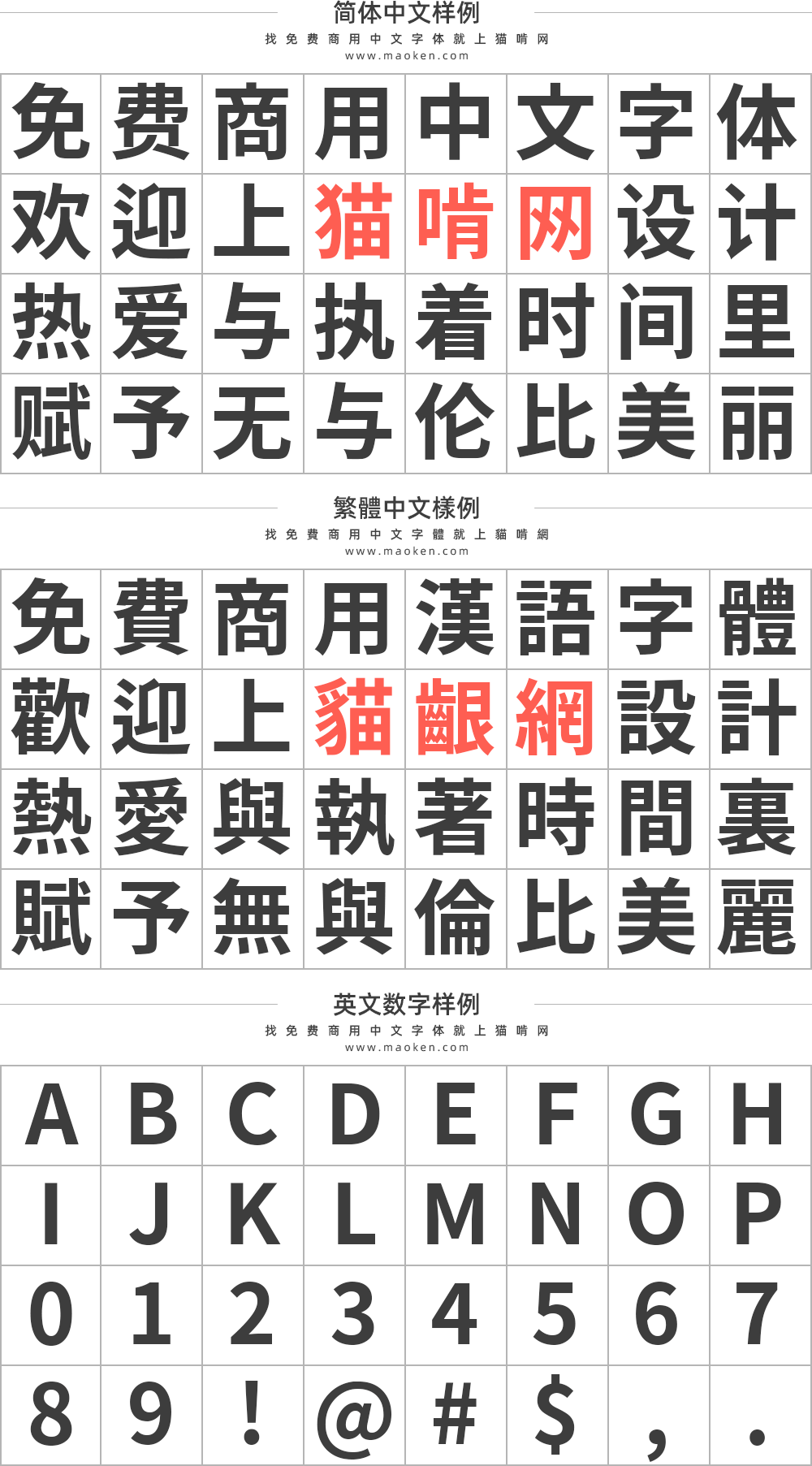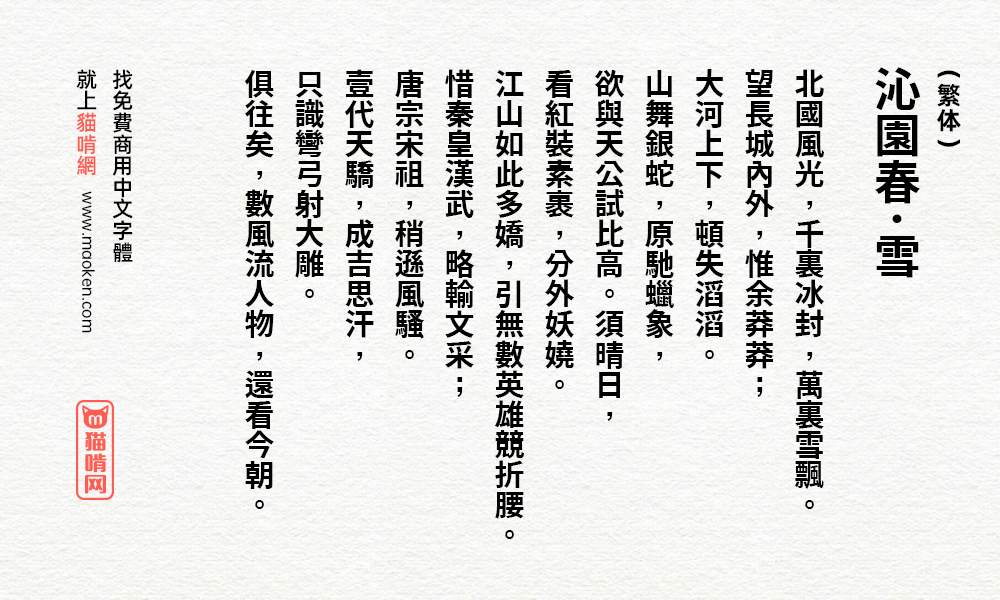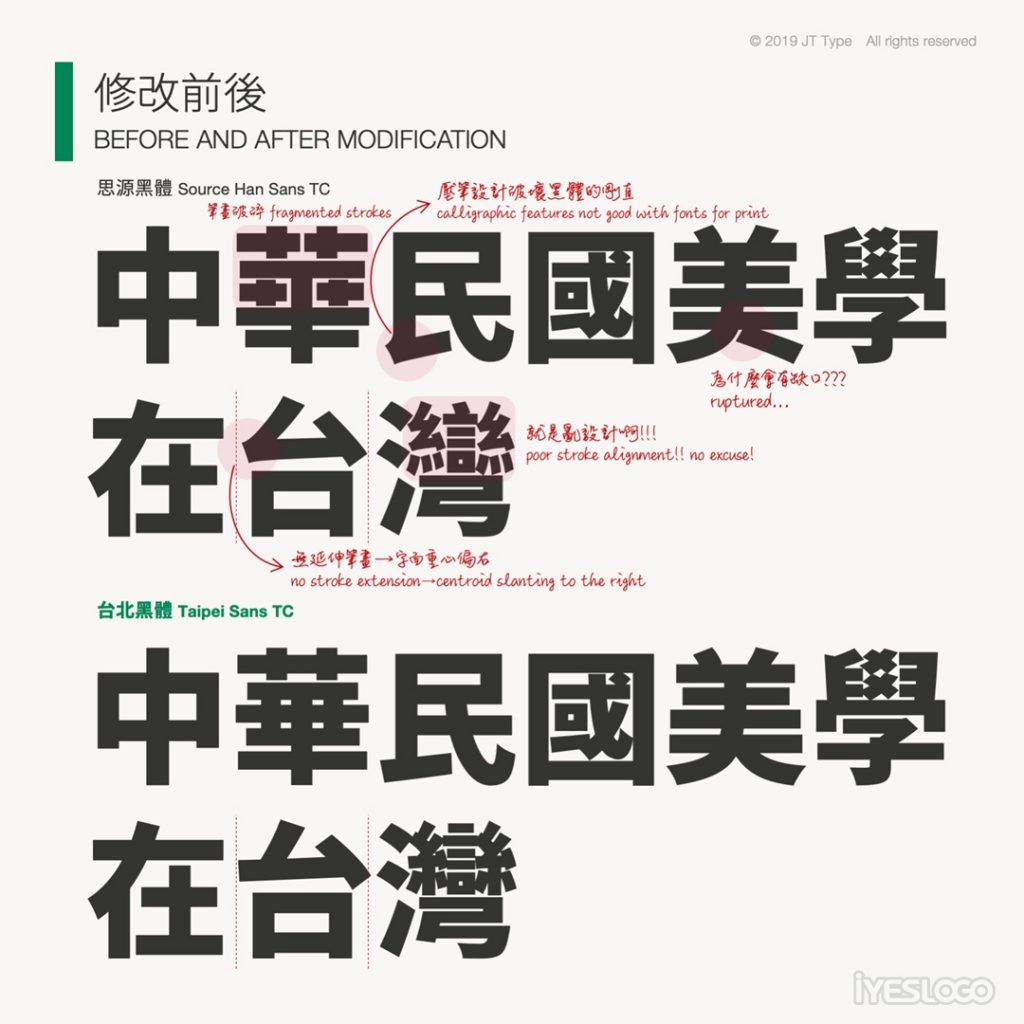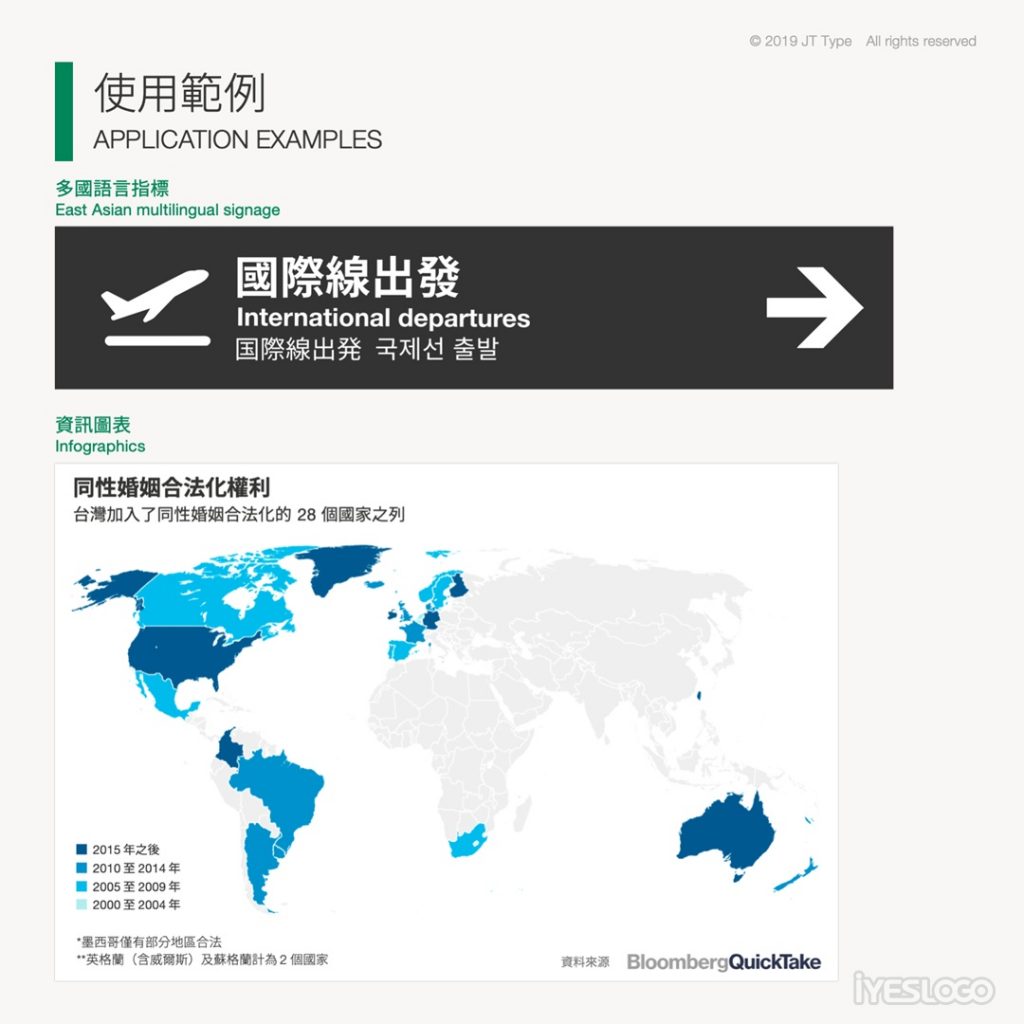
台北黑体:来自宝岛台湾的思源黑体改进版 免费商用
字体作者:翰字铸造 (中国台湾) 字体字重:3个
说到免费可商用的中文黑体字型,大家第一印象可能都会是 「 思源黑体 」 , 「 阿里巴巴普惠体 」 等,现在又多了个 「 OPPO Sans 」 !。但很多用户反馈 「 思源黑体 」 的繁体字其实有好多设计问题,且有些字体虽然适用性比较强,但同时也失去了个性,甚至不太适合在印刷场景使用。
今天和大家分享一款来自台湾的免费开源字体「台北黑体」。台北黑体 (Taipei Sans TC) 是由“翰字铸造”2019 年新推出的一款繁体字体,以思源黑体为基础进行优化设计,让繁体中文的使用者也能有适用于不同情境的印刷风格黑体,运用于平面稿时,效果更为漂亮。
1.此为 Beta(公测)版本
翰字铸造未来将持续进行字型改作,以满足更多繁体中文世界的使用需求。目前台北黑体拥有三个字重 light、regular、bold,预计在 2020 年底前推出剩余的字重 extralight、normal、medium、heavy。
2.「汉字几乎不缺字」的意义
台北黑体的改作基于思源黑体的 KR 版。繁体中文世界日常生活所需的汉字都已尽量统一为印刷风格并符合当代习惯。
台北黑体保留思源黑体所支持之所有汉字(包含简体字、日本汉字、韩国汉字)及日文假名,惟部分未包含于 KR 版的汉字仍会维持 TW 或 CN 版的写法。
字体设计理念
台北黑體=新舊字形混合 對標商業字體 華康黑體
昭源黑體=新字形 對標商業字體 蒙納黑體
源樣黑體=舊字形